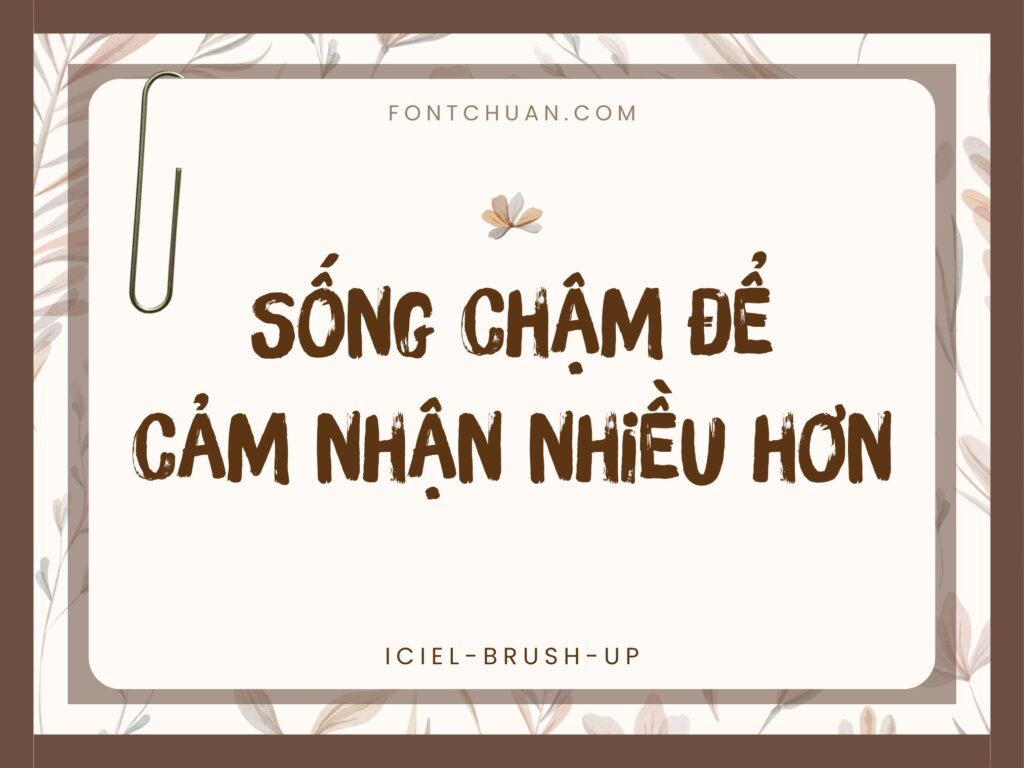
Font iCiel Brush Up Việt Hóa
Brush Up là một font chữ viết tay độc đáo, được thiết kế bởi Erica Jung và Ricardo Marcin, mang lại cảm giác tự nhiên và phóng khoáng cho các dự án thiết kế. Font này được vẽ nhanh trên giấy và chuyển đổi cẩn thận thành dạng số, cung cấp ba biến thể cho mỗi chữ cái và hai cho mỗi chữ số, cùng với các biến thể cho một số dấu câu. Để hỗ trợ cộng đồng thiết kế Việt Nam, Iciel đã Việt hóa font Brush Up, giúp font này hỗ trợ đầy đủ tiếng Việt cùng hơn 200 ngôn ngữ khác. Phiên bản Brush Up Việt hóa đã được thành viên Font Chuẩn sưu tầm và đăng tải, mang đến sự lựa chọn phong phú cho các nhà thiết kế.
Về đặc điểm thiết kế, Brush Up sở hữu các ký tự với nét vẽ tay mạnh mẽ và tự do, tạo nên sự linh hoạt và sinh động cho văn bản. Font này rất phù hợp cho các thiết kế như poster, tiêu đề, bao bì sản phẩm, thiệp mời và các dự án cần sự sáng tạo và cá nhân hóa. Ngoài ra, Brush Up cũng là lựa chọn lý tưởng cho các ngành nghề như quảng cáo, giáo dục, ẩm thực và thiệp cưới, mang lại phong cách độc đáo và thu hút. Font này cũng thích hợp để sử dụng trong các sự kiện như Valentine, sinh nhật và các dịp lễ hội.